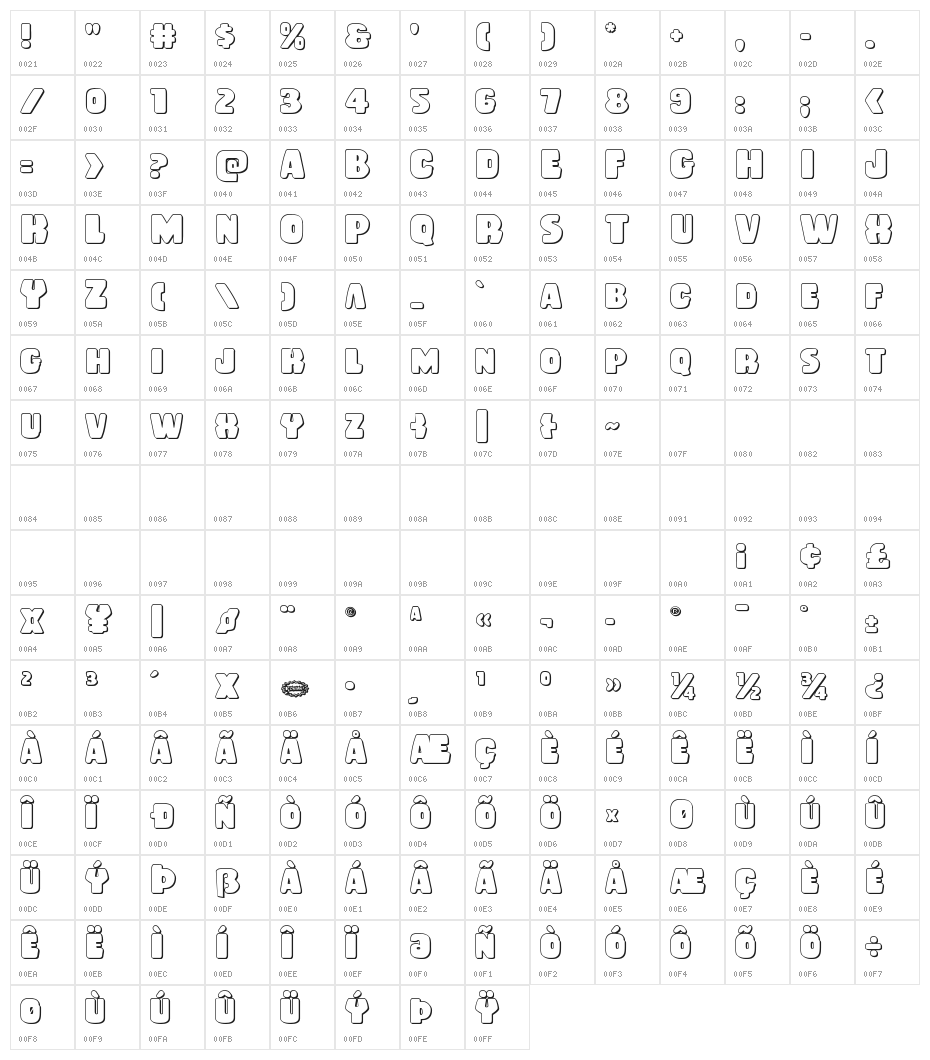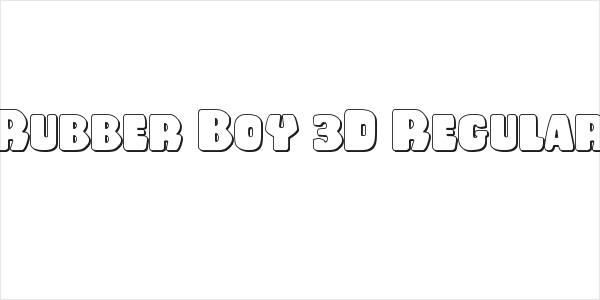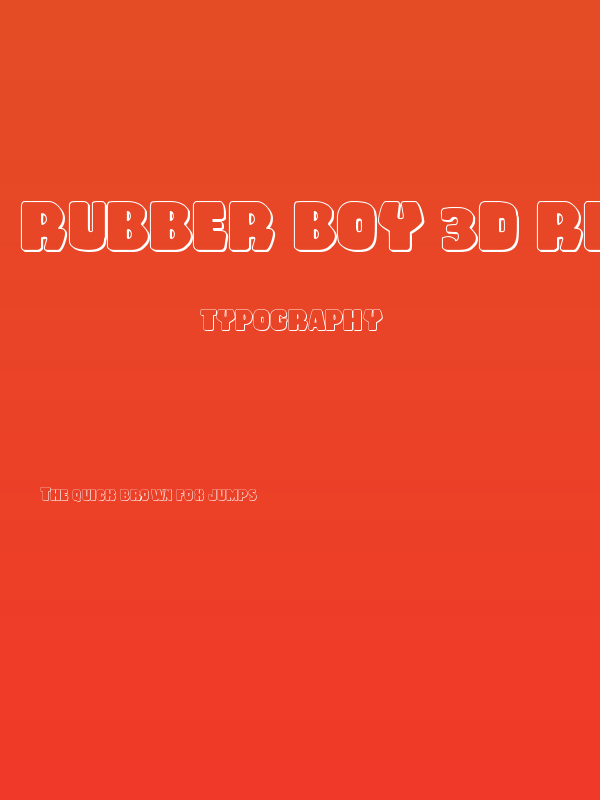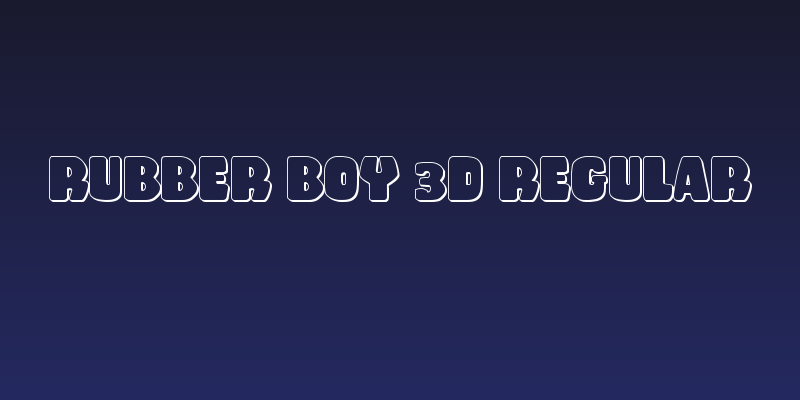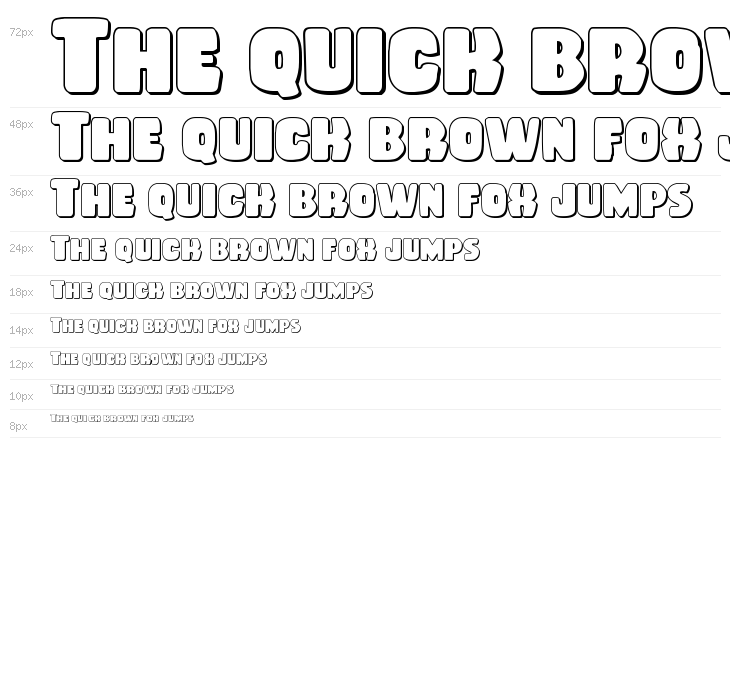
Rubber Boy 3D Regular Font
| Stile generale | Playful, Cartoonish, Fun |
| Progetti proposti | Ideal for children's book covers, playful posters, toy packaging, and fun branding materials. |